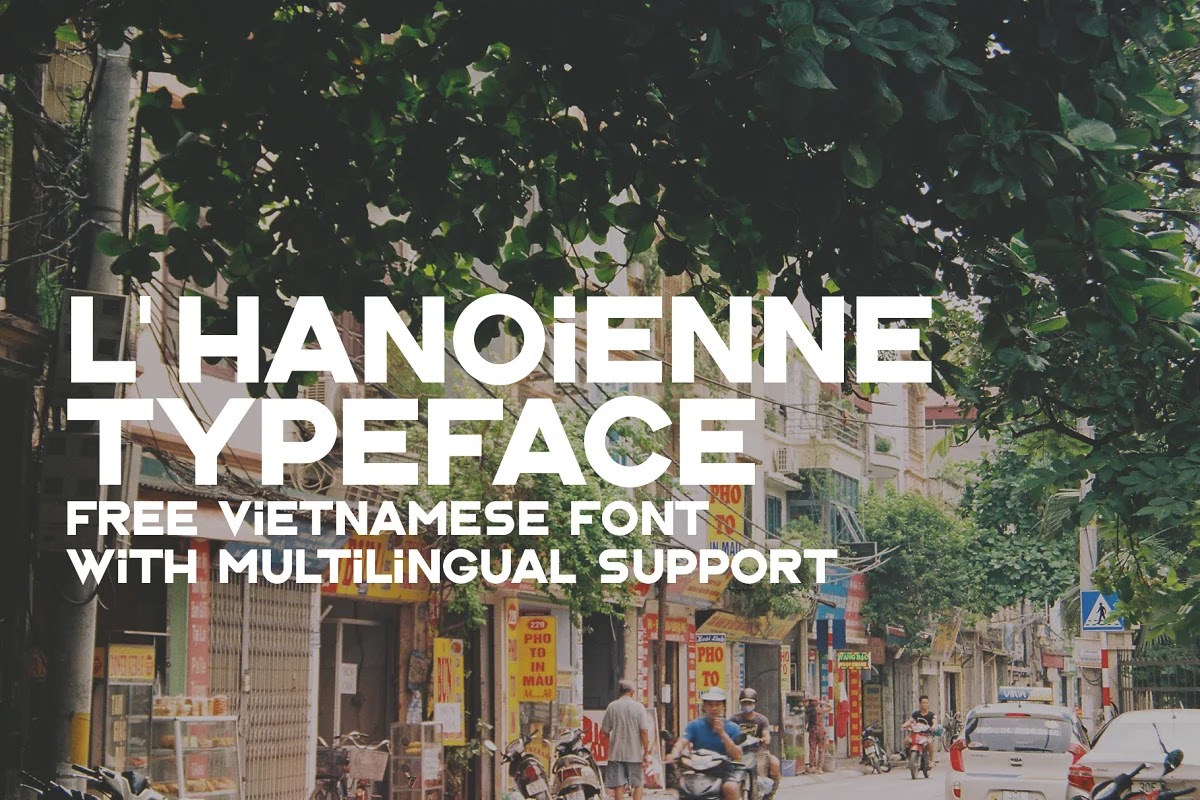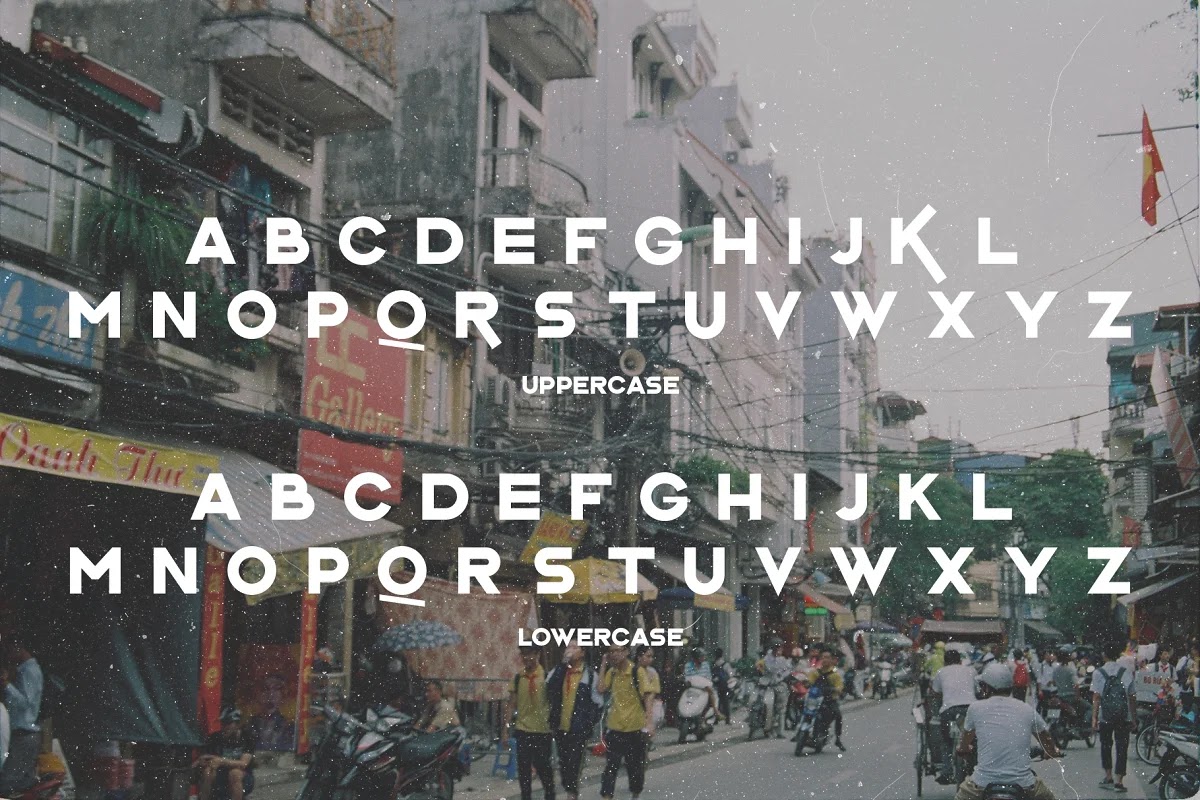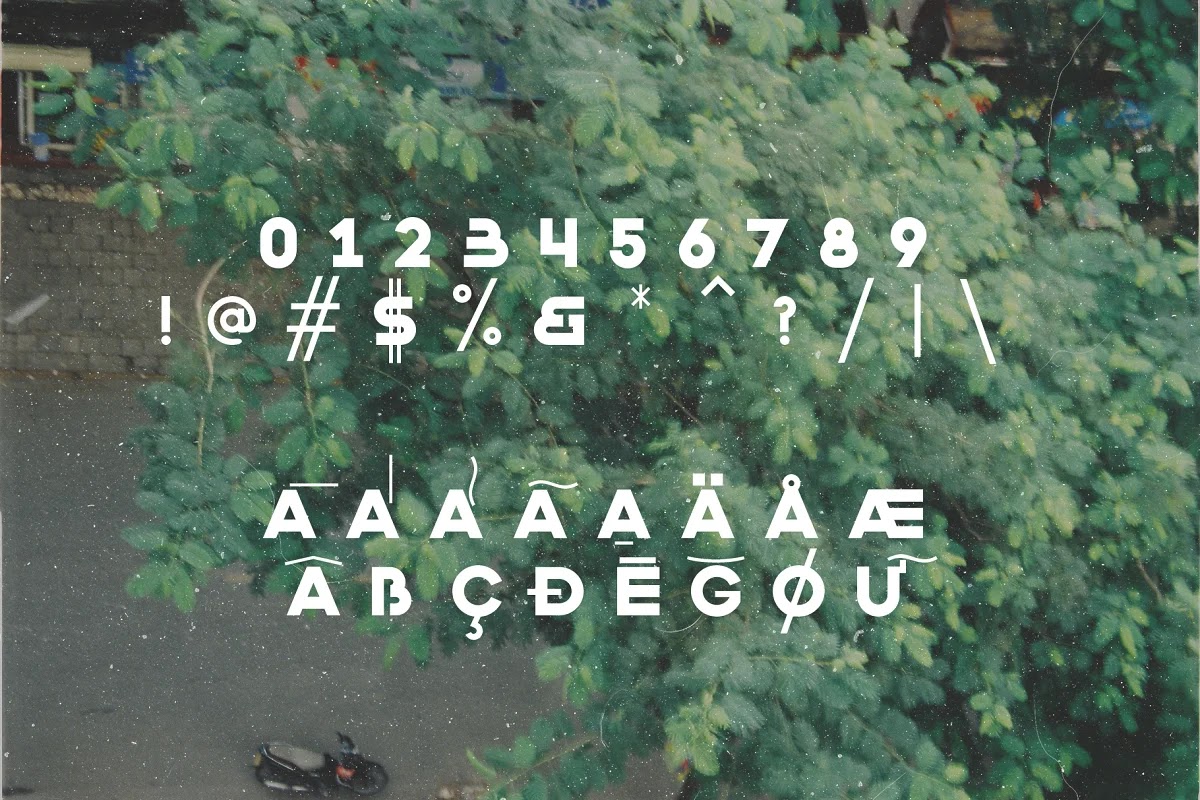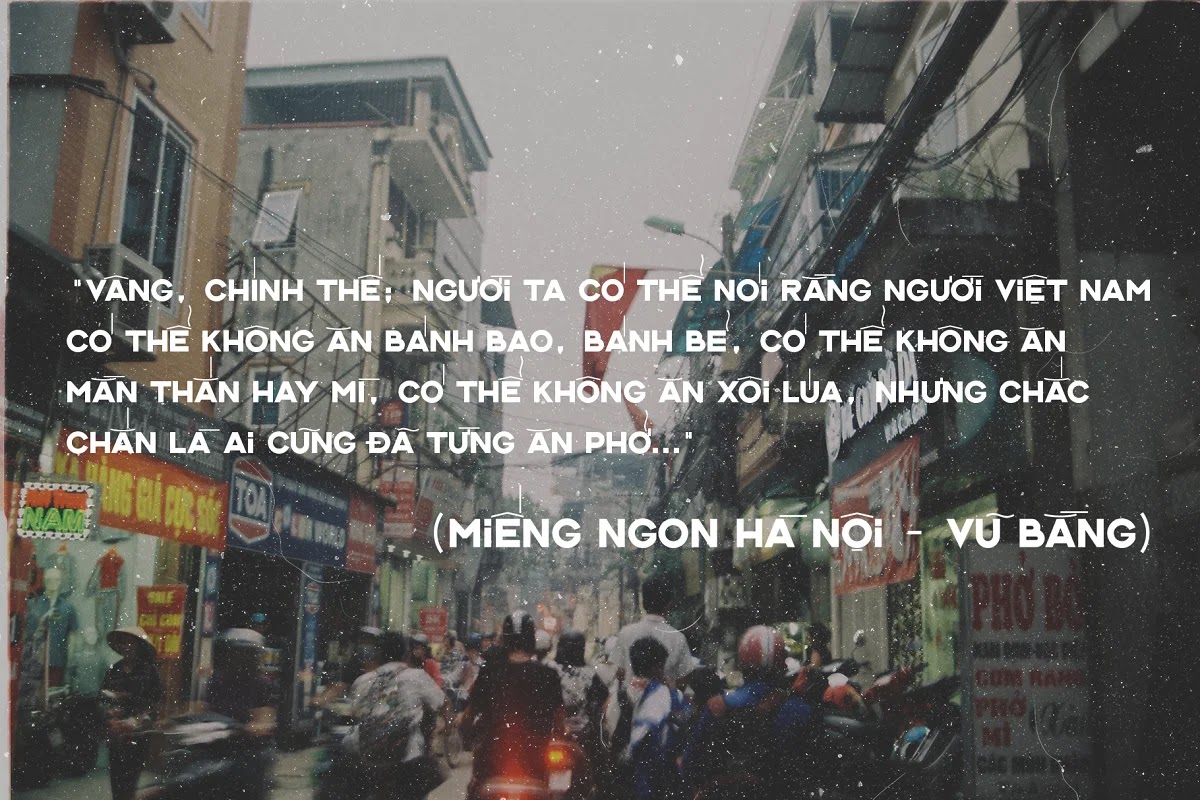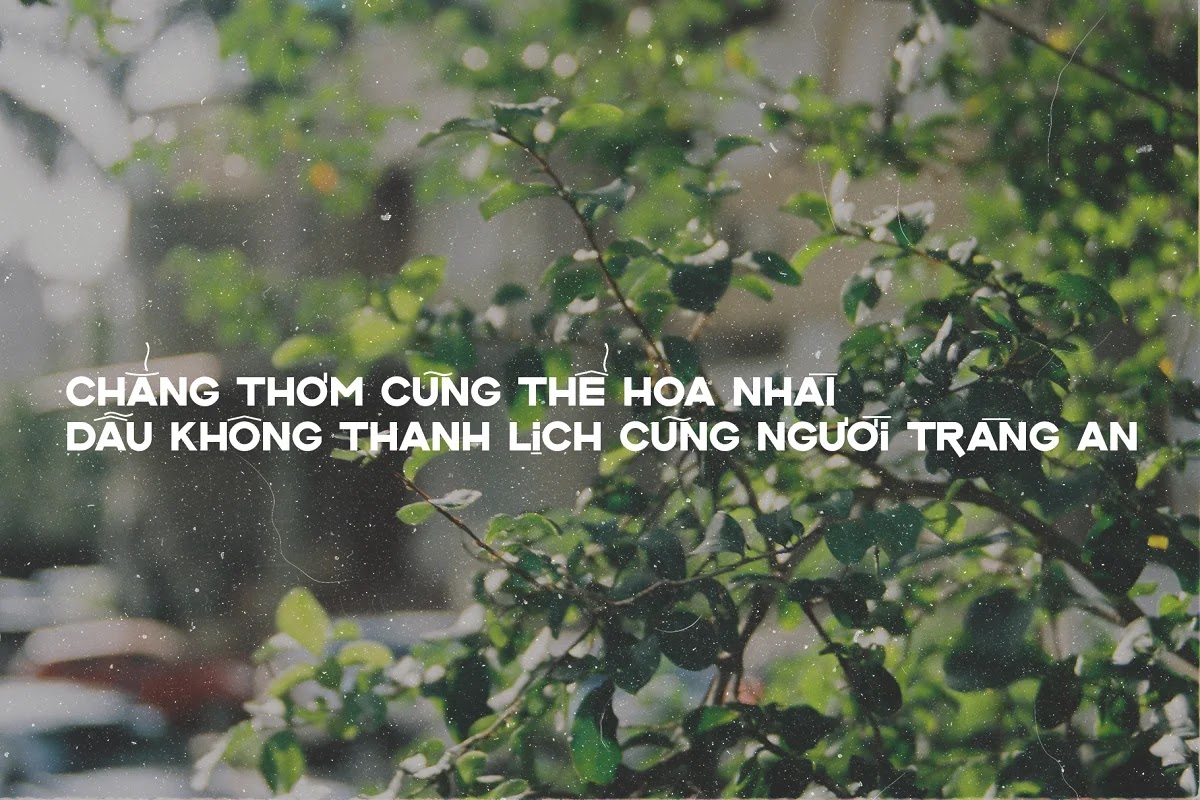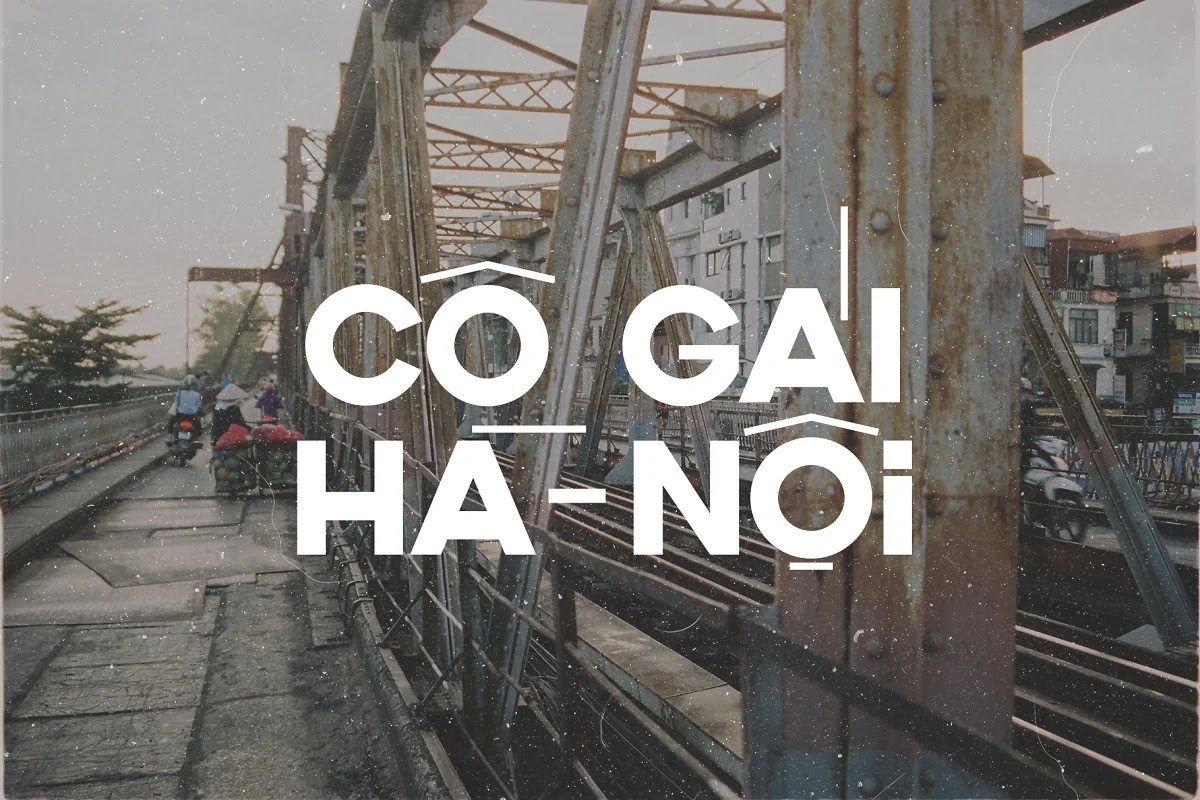
L’Hanoienne Typeface là một kiểu chữ tiếp trong dự án của Manh Nguyen. Font chữ với phong cách xưa cũ nhưng đầy tính tương lai của những tấm bảng và biểu ngữ vẽ tay theo phong cách cổ điển vốn là biểu tượng lâu đời trên đường phố Việt Nam vào thế kỷ 20.
L’Hanoienne, mặc dù có chung kiểu dấu và kiểu chữ với người anh em font Classique Saigon, nhưng vẫn có một số khác biệt lớn ảnh hưởng đến trải nghiệm đọc của người dùng. Được xây dựng như một sans serif hiện đại hình học như Classique Saigon, tuy nhiên, L ‘ Hanoienne có độ tương phản nhẹ nhàng và tinh tế hơn, phù hợp với vẻ đẹp Viễn Đông kín đáo và dịu dàng của người phụ nữ Bắc Kỳ thế kỷ 20.
Mặc dù là một loại hiển thị, L’Hanoienne cho thấy những rung cảm cổ điển tuyệt vời khi sử dụng làm nội dung văn bản bằng tiếng Việt.